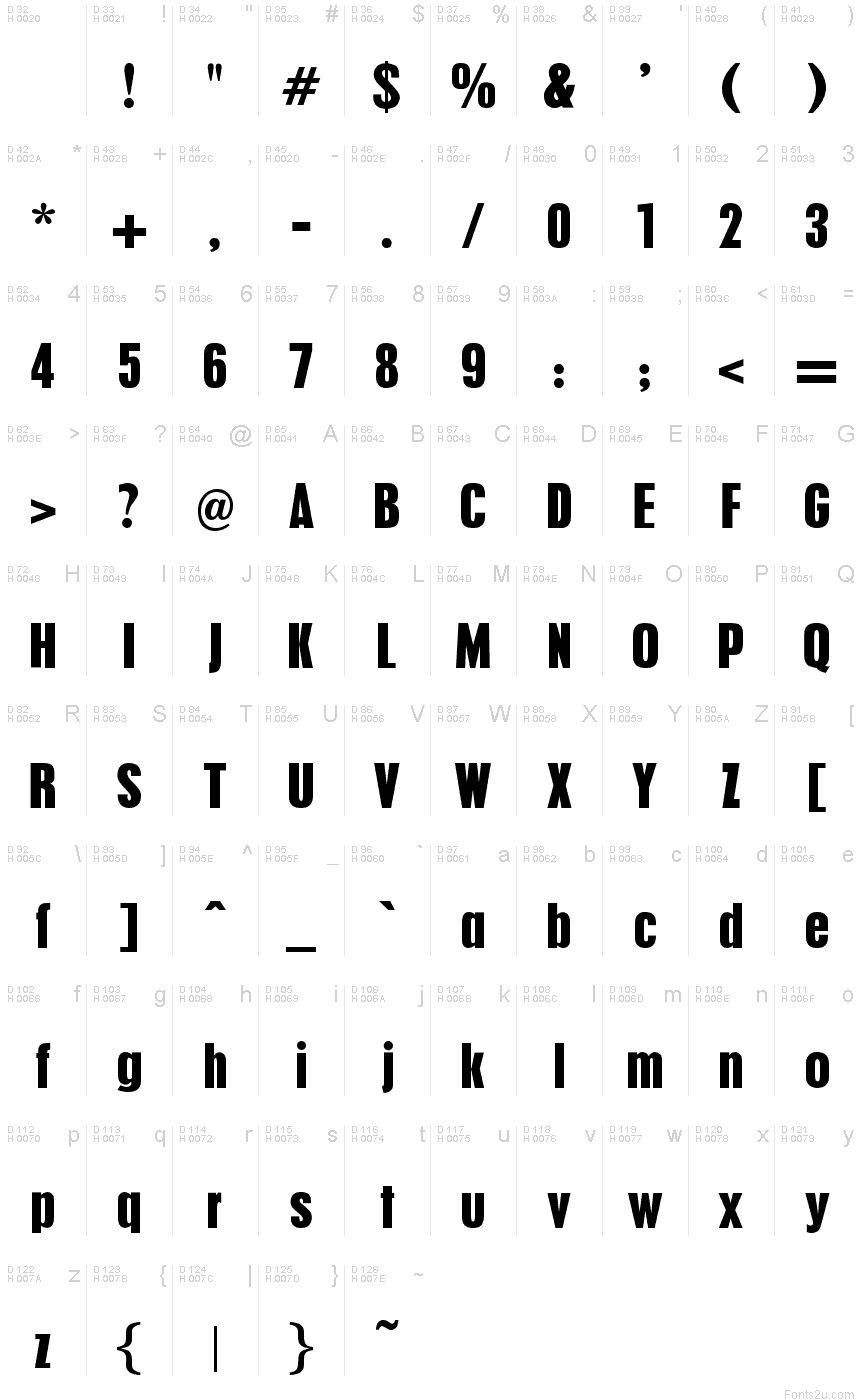
Pilsen Plakat
Pilsen Plakat, bezpłatny krój bezszeryfowy od Typographer Mediengestaltung, ma w sobie surową, zwartą energię ulicznych plakatów i dawnej typografii prasowej. Ciężkie piony, łagodne zaokrąglenia i kompaktowe litery tworzą solidny, bezpośredni rytm – widać w nim bardziej drukarski rodowód niż cyfrowy szlif.
Dzięki temu to naturalny wybór do tytułów na plakatach, ulotek muzycznych, etykiet piw, grafik eventowych i wyrazistych nagłówków, gdzie potrzebujesz gęstych, czarnych kształtów, które przykuwają uwagę. Sprawdza się też w krótkich tytułach i monogramach, ponieważ litery zazębiają się w blokowy sposób, sprawiając, że nawet krótkie słowa wyglądają solidnie i nabierają wagi.